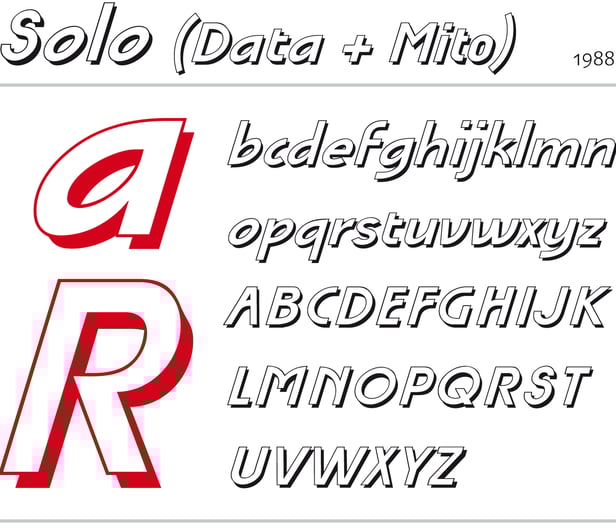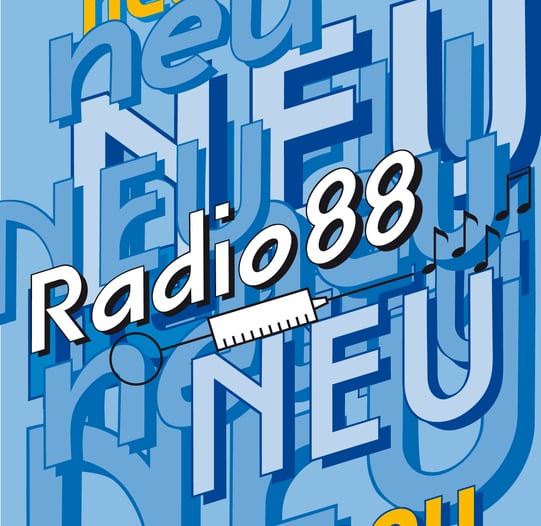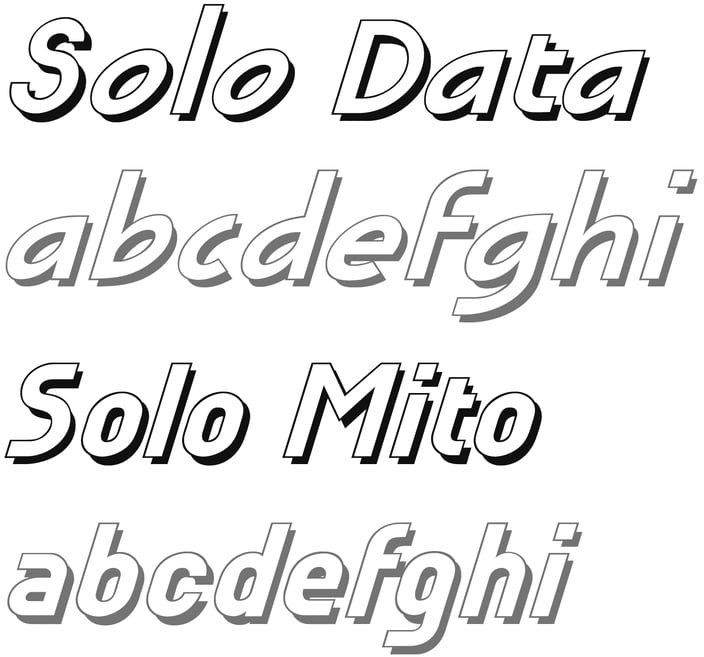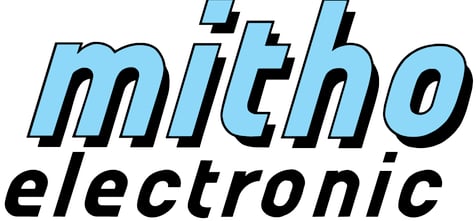
Solo (Data + Mitho)
Als Entwurf zu einem Schriftzug »Radio 88« für das Patientenradio im Kreiskrankenhaus Backnang entstand diese schattierte Auszeichnungsschrift. Zwar entschied sich der Kunde für eine andere Lösung, aber in zwei weiteren Fällen kam die Schrift dennoch zum Einsatz. Zunächst für »mitho electronic« in einer etwas modifizierten Form und dann für »Solodata« mit den schrägliegenden Rundformen. Erst viel später begann ich damit, aus den wenigen Buchstaben zwei komplette Alphabete zu machen, die sich auch ohne Probleme mischen lassen.